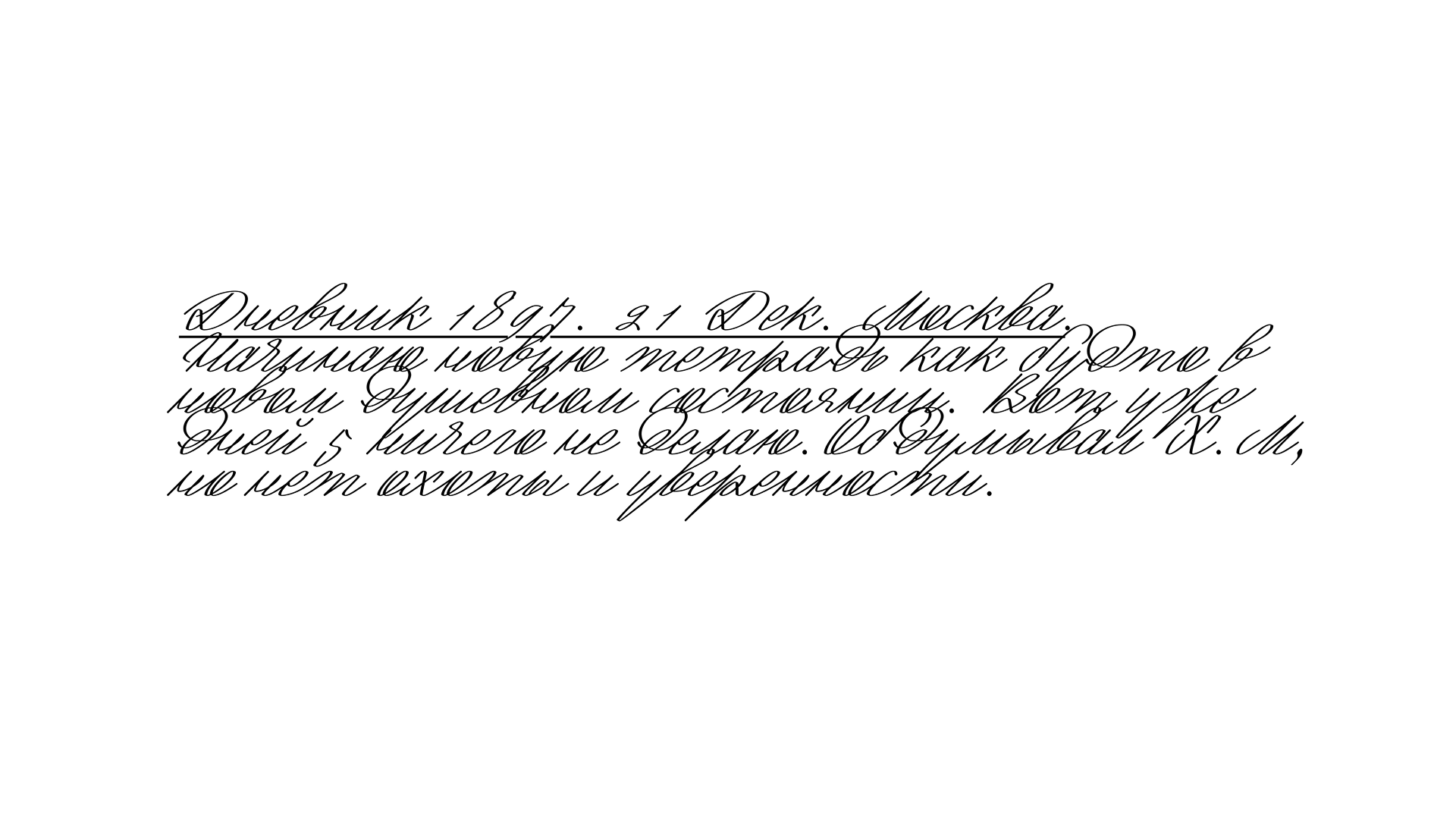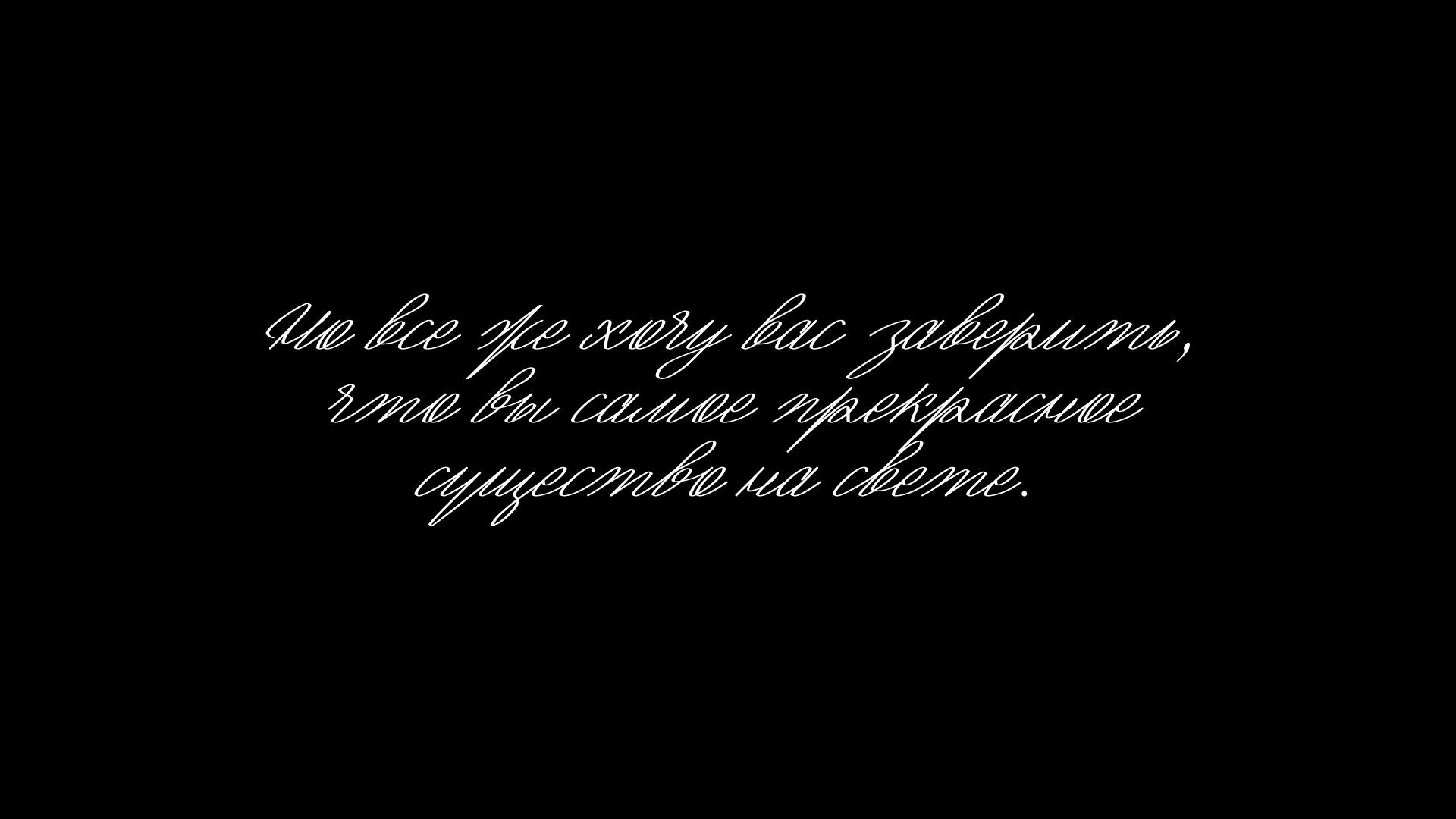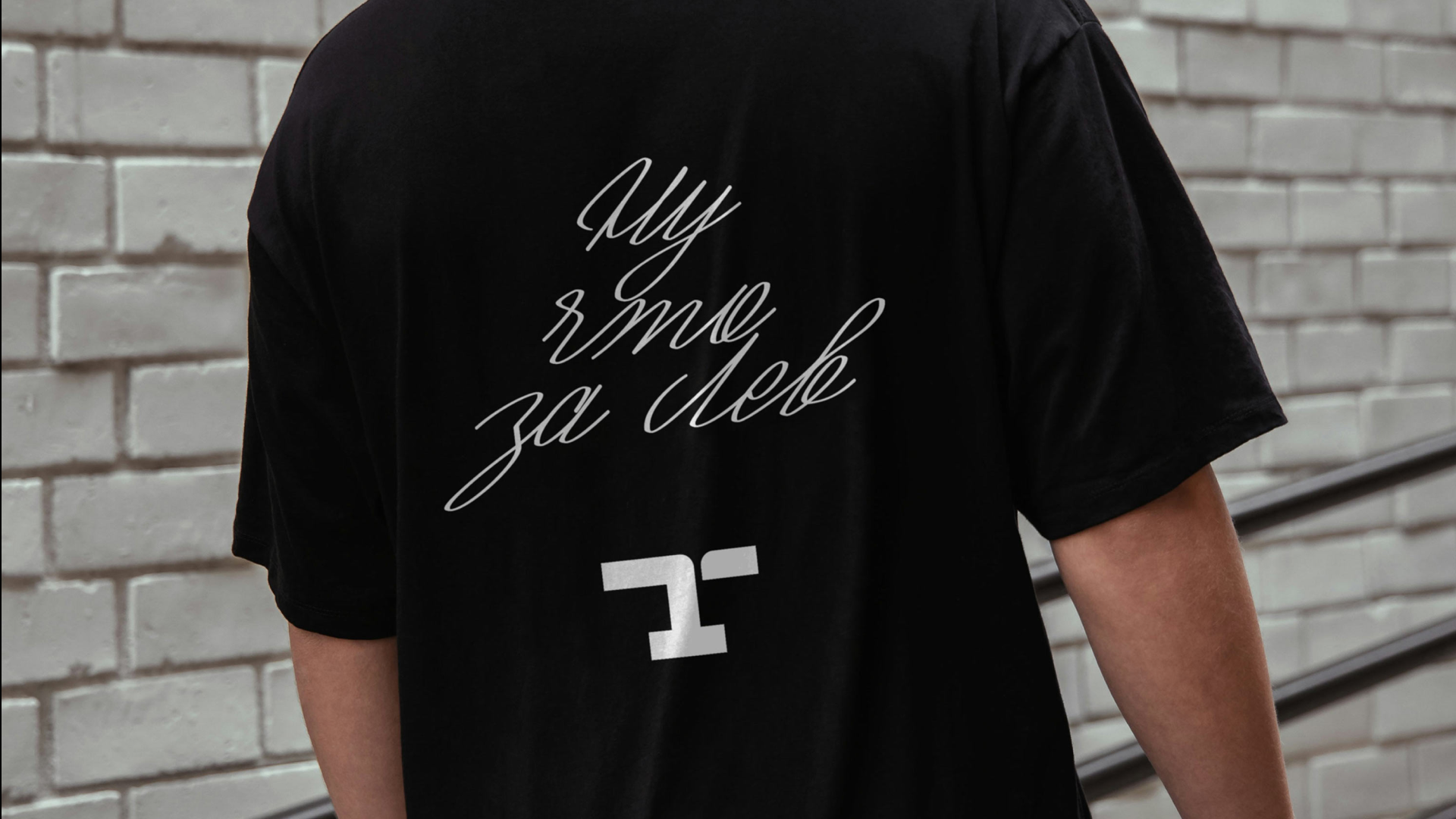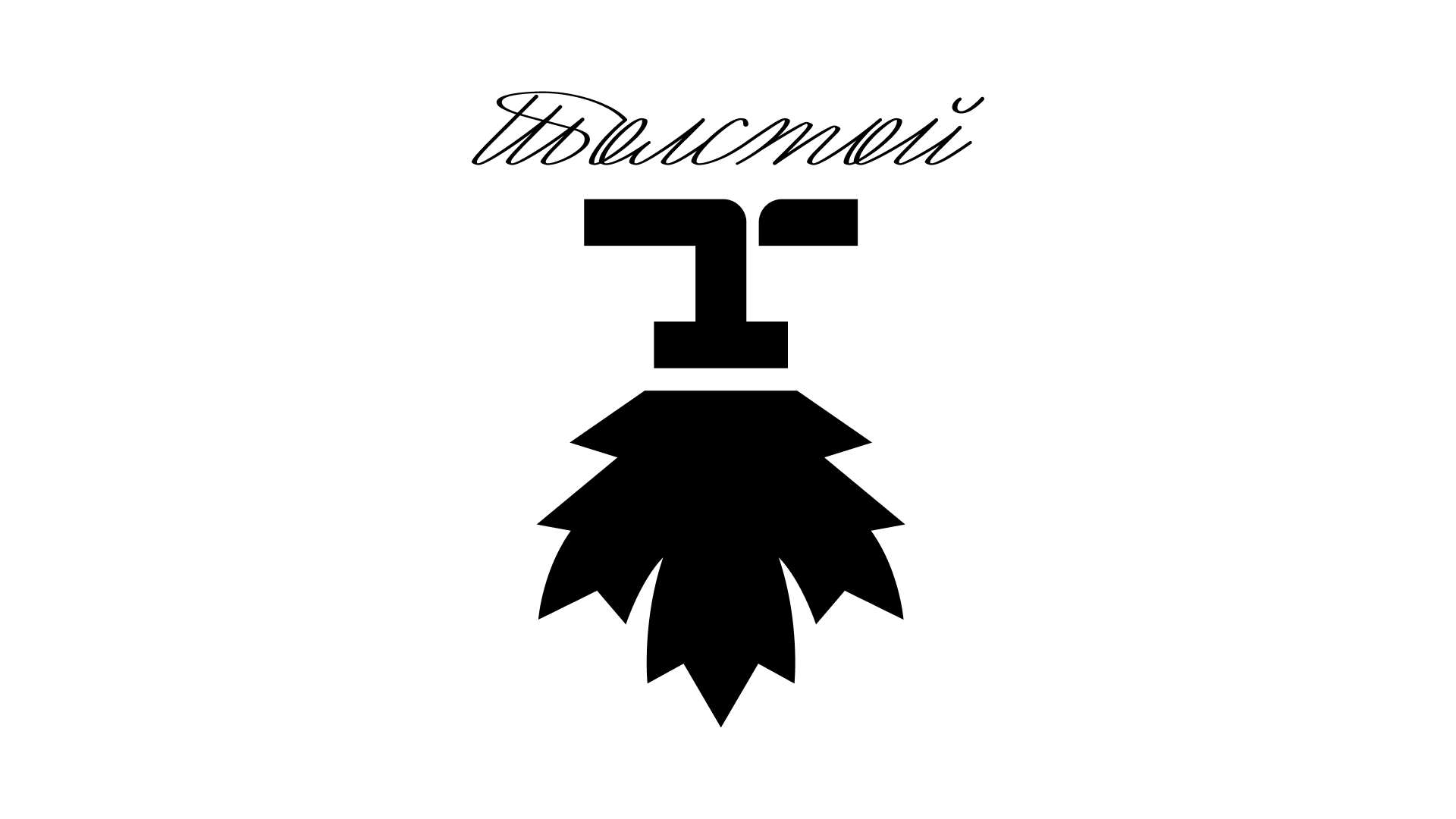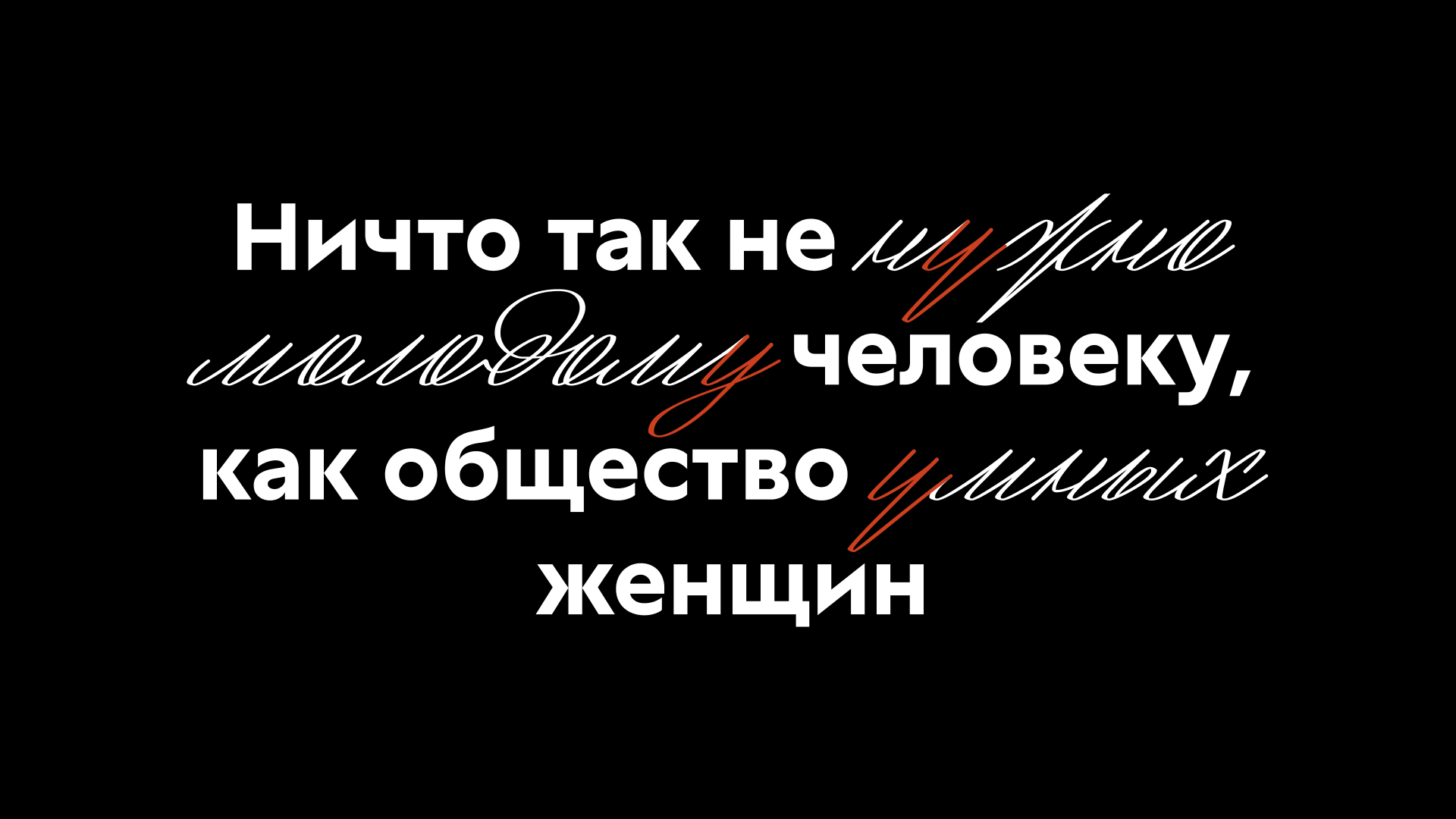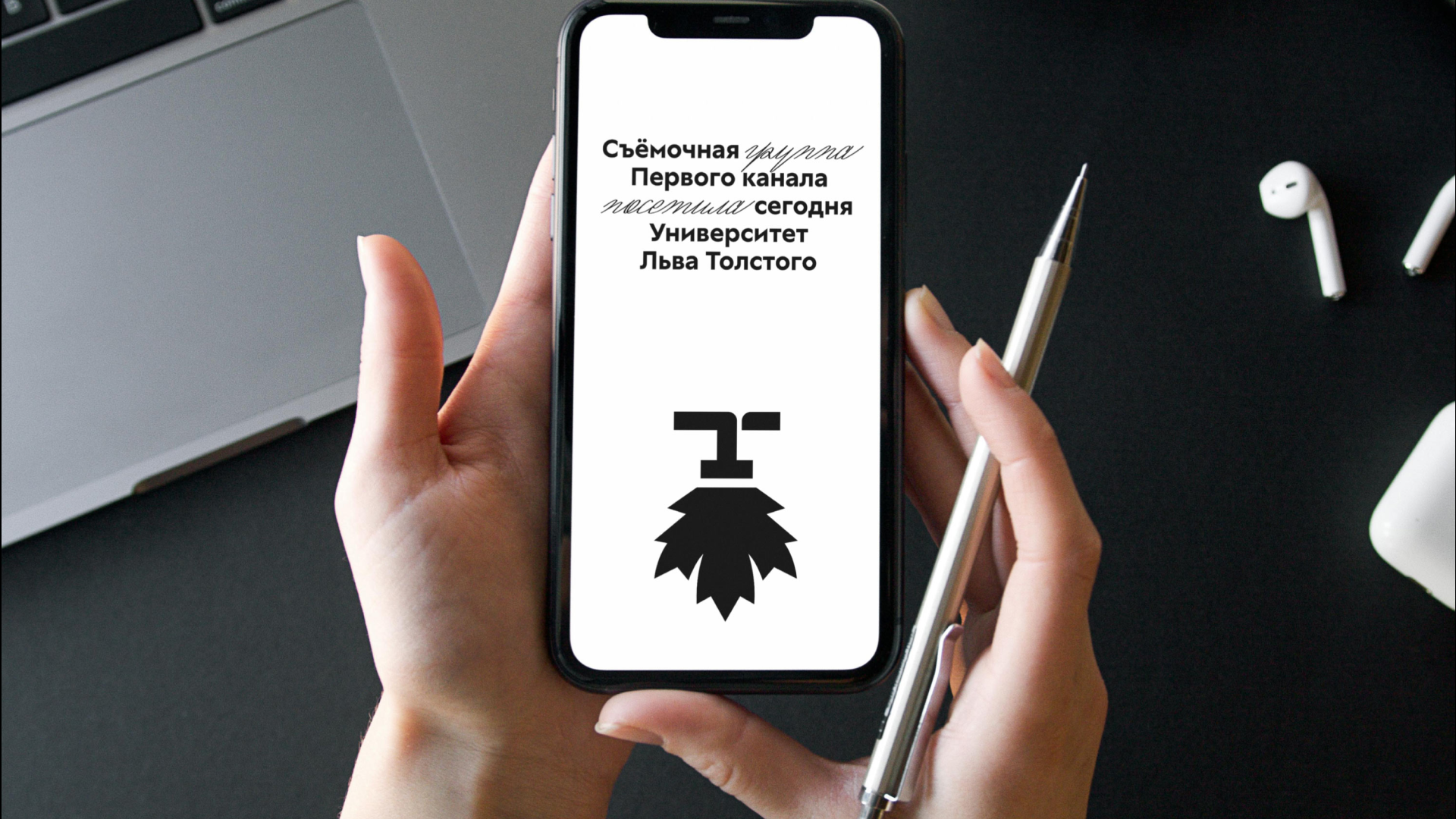
Шрифт Тульского государственного педагогического университета им. Л. Н. Толстого
Толстой — декоративный акцидентный шрифт, который мы создали специально для Тульского государственного педагогического университета им. Л. Н. Толстого на основе анализа архивных документов и почерка великого писателя в процессе разработки айдентики учебного заведения.
Резкость и экспрессия в шрифте достигаются за счет заостренных скруглений овалов и длинных угловатых выносных элементов. Все основные вертикальные штрихи и овалы имеют постоянный наклон в 45 градусов — как и в почерке Льва Николаевича.
Бывает, что на письме одна и та же буква в разных позициях воспроизводится по-разному — так делал и классик. Поэтому в Толстом формы букв З и У отличаются в закрытом и открытом положении.
Тульский государственный педагогический университет им. Л. Н. Толстого